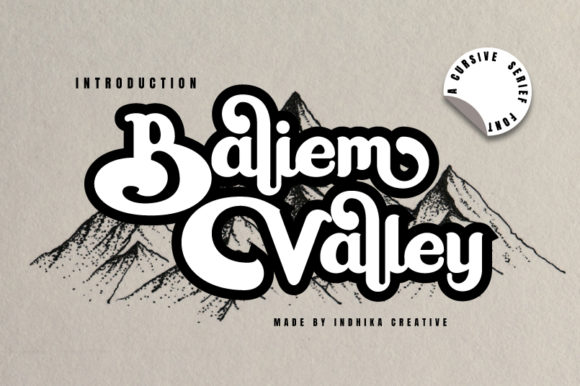
Creativefabrica Baliem Valley Font
[Creativefabrica] Baliem Valley Font
Baliem Valley - это прохладный шрифт в ретро-стиле.
Этот оригинальный вид будет привлекать широкий спектр хитроумных идей, от бланков и титулов, до канцелярских принадлежностей.